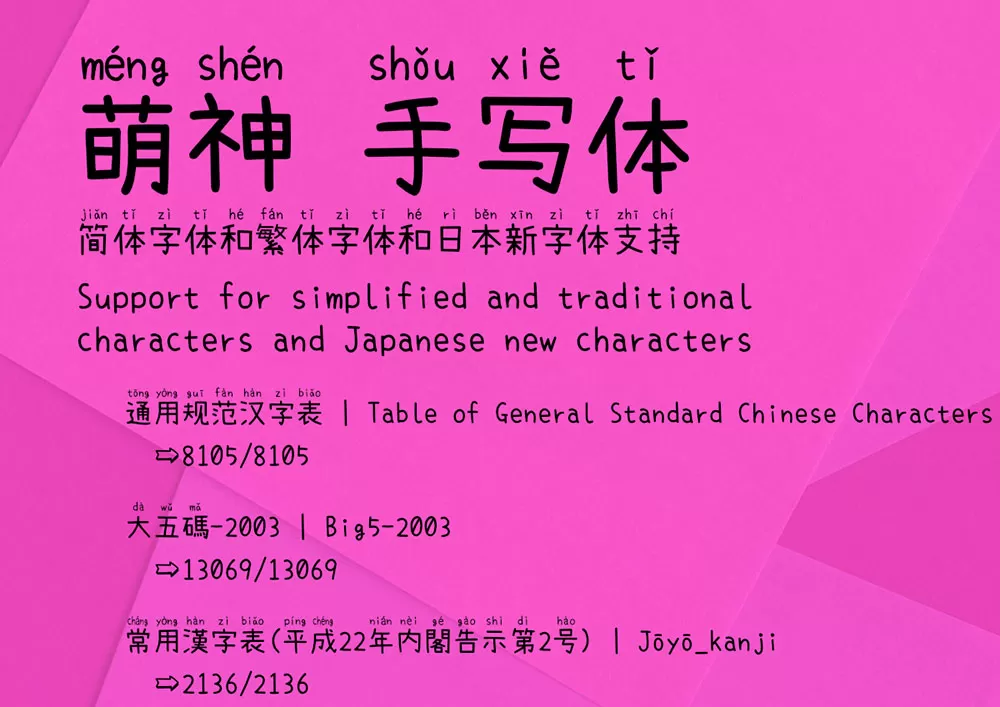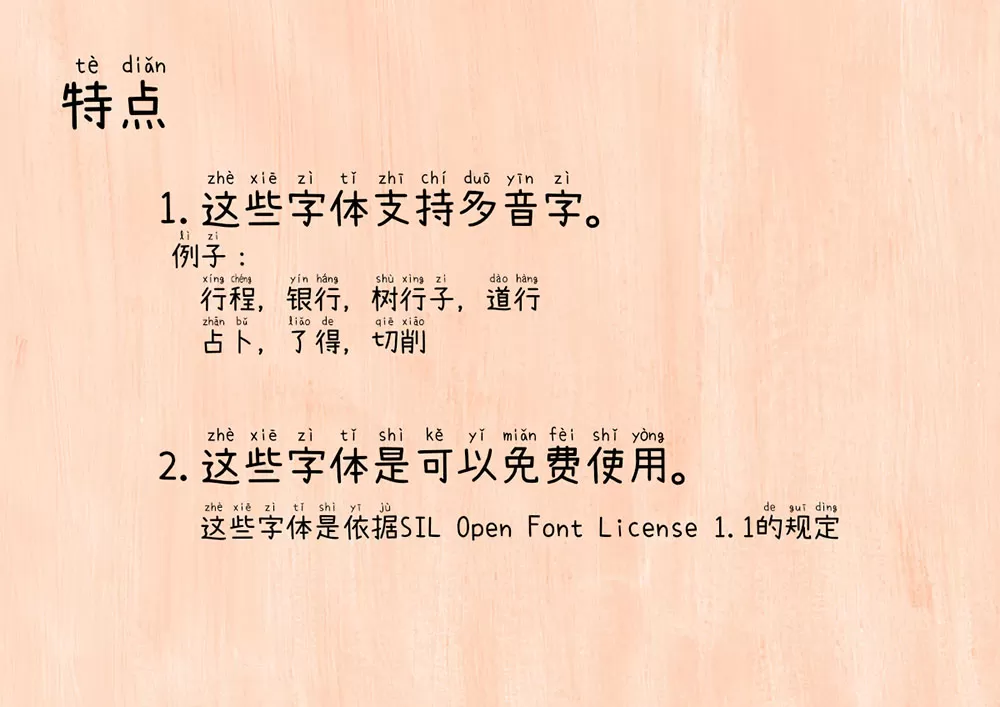
萌神手写体
字体介绍
萌神手写体是一款基于“小赖字体”改造的拼音字体,采用亲切自然的手写风格,并自带拼音注音功能。它不仅支持智能多音字识别,还遵循 SIL Open Font License 1.1 开源协议,允许用户免费使用、修改与分享。
该字体全面覆盖基础日语、简体中文与繁体中文,并专门为简繁汉字均添加了拼音标注,尤其适合汉语学习者使用,能有效辅助识字、提升阅读效率。
在技术实现上,萌神手写体通过上下文替换(GSUB 中的 “rclt” 特性)来支持多音字显示。用户还可借助 Unicode IVS(表意文字变体选择器)灵活切换不同的拼音读音。
萌神手写体示例一萌神手写体示例二